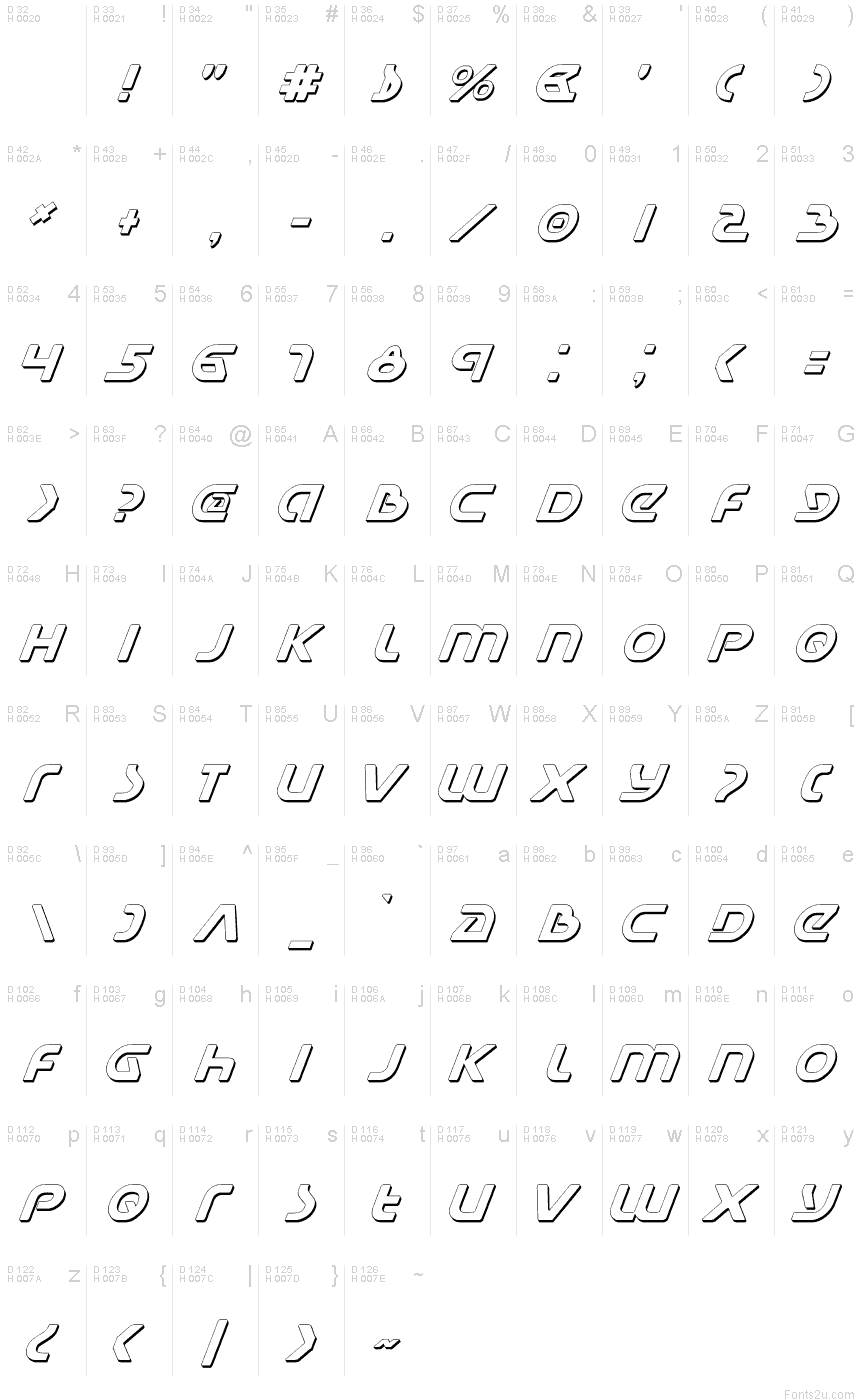
Universal Jack Shadow Italic von Iconian Fonts ist eine kostenlose, futuristische Display-Schrift mit einer rasanten, geneigten Silhouette und einem scharfen, versetzten Schatten. Die Buchstaben wirken stromlinienförmig und leicht techno-inspiriert, mit abgerundeten Ecken, weiten Kurven und spitzen Verbindungen, die der Schrift einen eleganten Sci-Fi-Look der frühen 2000er verleihen, ohne dabei überladen zu wirken.
Sie fügt sich natürlich in Gaming-Logos, Plakatüberschriften, Musik-Artworks, Titelkarten und Tech-Branding ein, wo eine kostenlose Schriftart benötigt wird, die Bewegung direkt in die Buchstaben integriert. Da der Schatten Teil des Designs ist, eignet sie sich auch hervorragend für kurze Schlagzeilen, Cover-Texte und Wordmarks, die Tiefe und einen schnellen Schuss Retro-Futurismus benötigen.